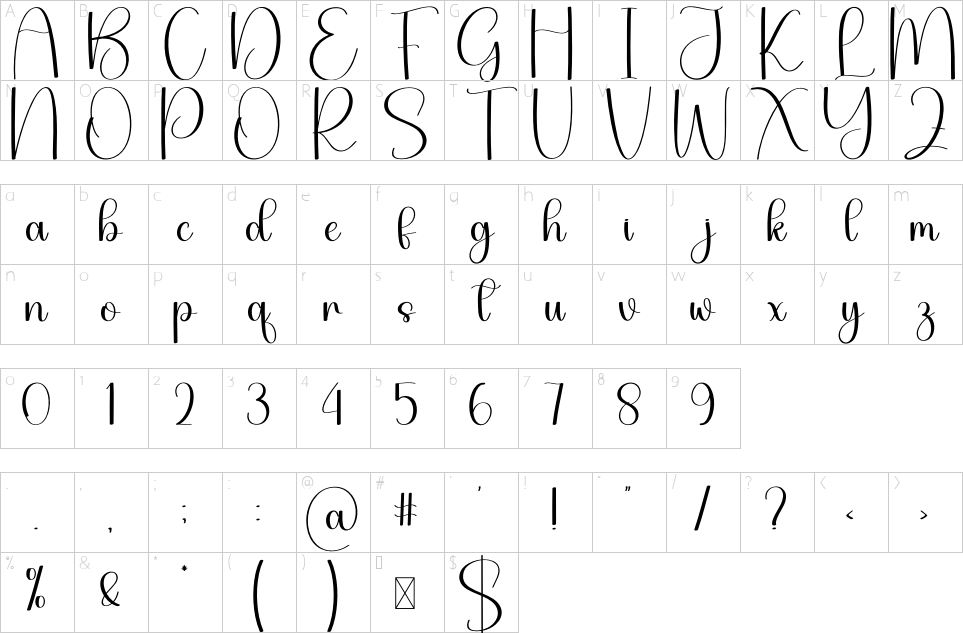
Esta página de download da fonte ‘Justify Font | 1001 Free Fonts’ apresenta uma seleção de fontes gratuitas que podem enriquecer qualquer projeto de design gráfico. ‘Justify Font’ é uma adição fantástica para qualquer designer que procura uma fonte moderna e moderna. Desenvolvida pelo designer desconhecido, ‘Justify Font’ foi projetada para oferecer uma variedade de opções de estilo, permitindo que você personalize o visual do seu projeto de acordo com suas necessidades. Além disso, esta fonte é compatível tanto com sistemas Windows quanto com Mac, tornando-o um recurso universal para designers de todo o mundo. Com mais de 335 downloads, ‘Justify Font’ já foi avaliada positivamente por designers de todo o mundo, o que a torna uma fonte de confiança para qualquer projeto. Não perca mais tempo, explore ‘Justify Font’ e encontre a fonte perfeita para o seu próximo projeto.